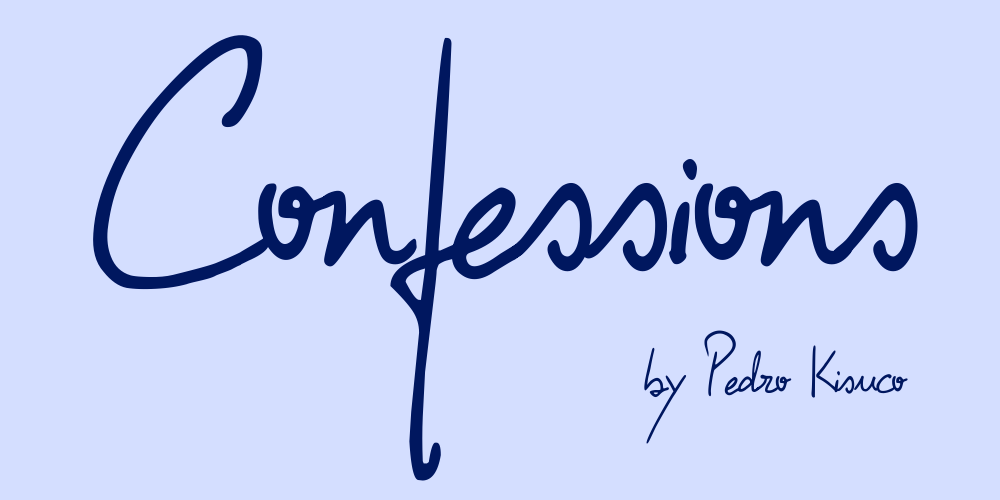
A fonte ‘Confessions’ oferece uma experiência única para os criadores digitais que desejam adicionar um toque autêntico e elegante a seus projetos. Desenvolvida pelo designer Hamilton, esta fonte script captura o jeito sofisticado de escrita que é tão comum no Brasil, particularmente em comunidades urbanas do Rio de Janeiro ou São Paulo. Suavemente fluida e flexível na forma dos caracteres, ‘Confessions’ se destaca por sua capacidade de expressar sentimentos e emoções através da letra. Perfeita para aplicativos de mídia social, mensagens pessoais, logotipos de marcas brasileiras ou até mesmo como uma fonte de texto no blog de um criador local, esta fonte é o alicerce perfeito para projetos que valorizam tanto a simplicidade quanto a expressividade. Com sua design puramente brasileiro, ‘Confessions’ se destaca por trazer um sabor autêntico à qualquer projeto que escolha adicionar. Seja em uma página de blog sobre cultura local ou até mesmo em mensagens pessoais escritas a mão, esta fonte promete manter o estilo e o charme brasileiro inerente.